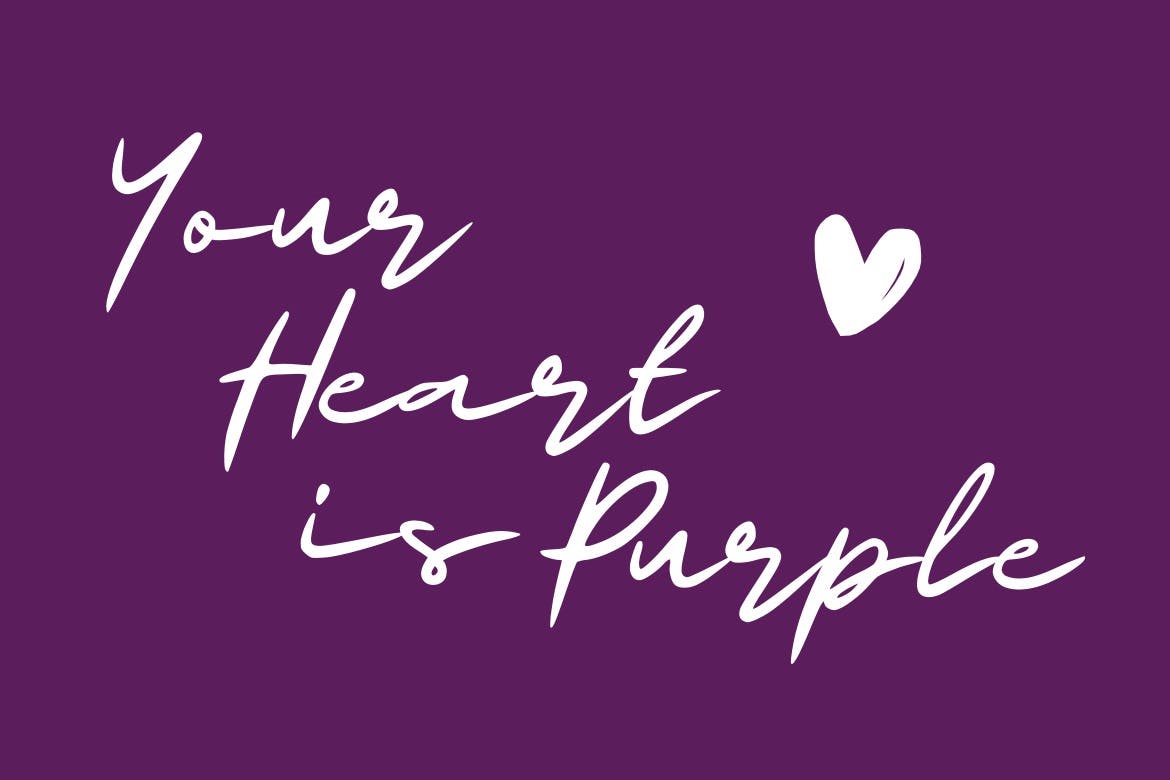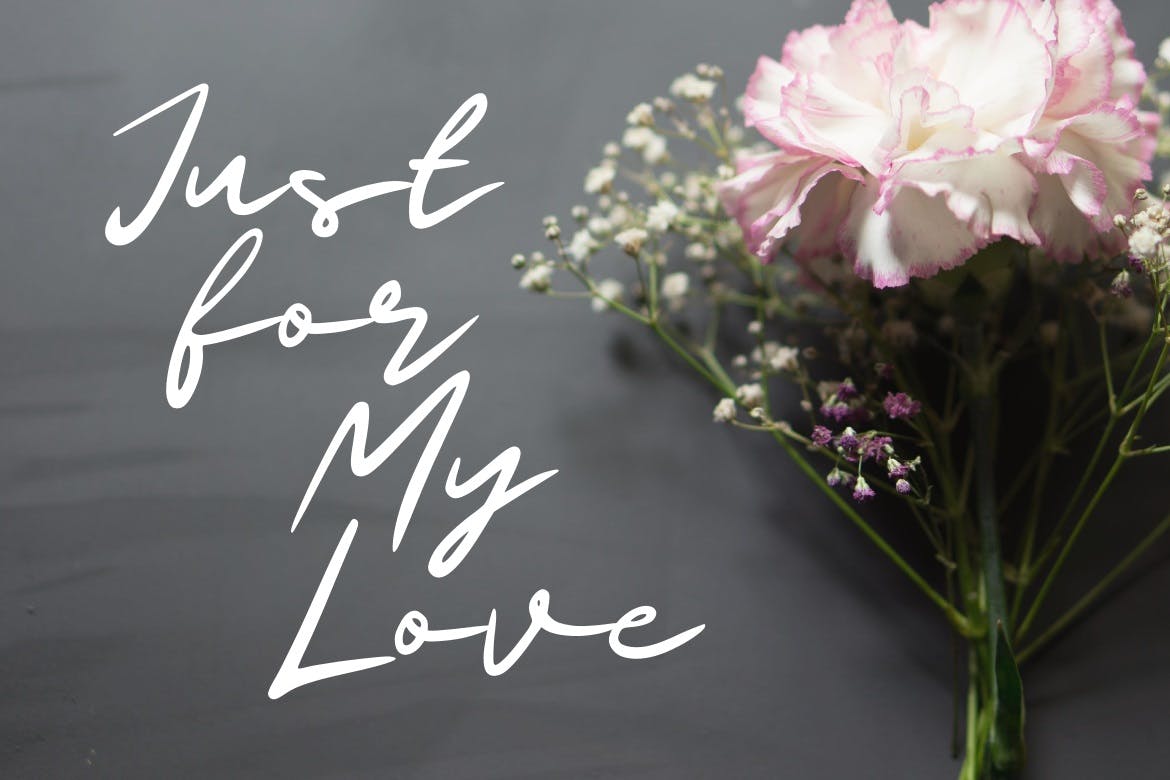
فونت Majesty
فونت Majesty یک فونت ساده و لوکس است که برای پروژههای مختلف، شامل نقل قولها، لوگوها، طراحیهای دودی، سرعنوانها و عناوین بسیار مناسب میباشد.